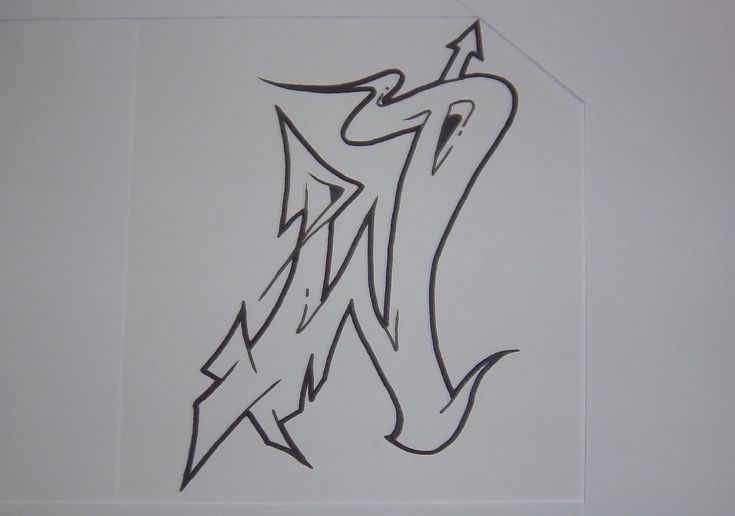
Граффити Буква N Азбука, граффити, рука, логотип, граффити png
Добавьте детали, такие как тени и небольшое свечение пузырьков!Шаг 6
Если вы хотите добавить такие детали, как тени и небольшое свечение пузырьков, добавьте их сейчас!
Следуйте простым шагам, чтобы написать букву N из пузырьков!Скачать и распечатать pdf-файлы для Bubble Letter N Учебник: